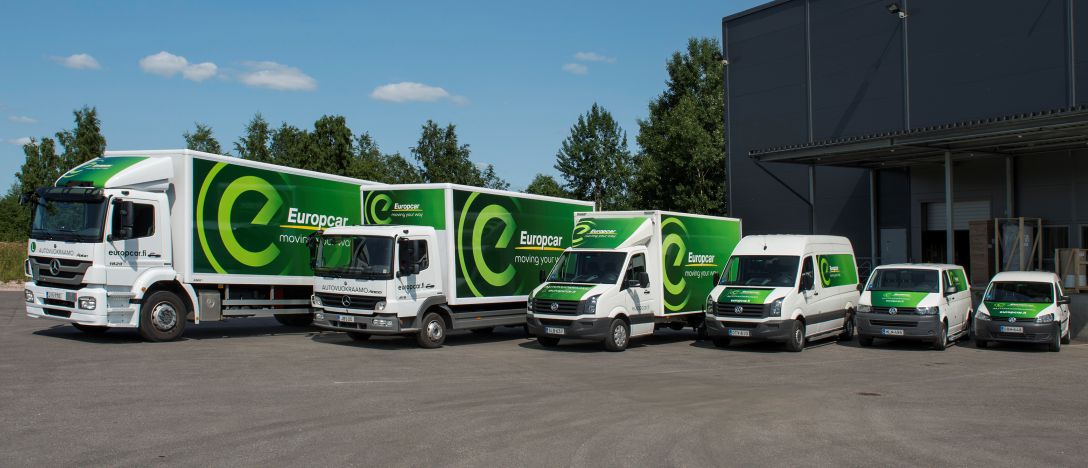
Auch ich habe das e gleich als solches erkannt. Warscheinlich weil hier in der Gegend vermehrt LKW von Europcar unterwegs sind:
Obwohl man natürlich fairerweise sagen muß: Wenn man all die dort inkriminierten Elemente konsequent meidet, wird die Luft ziemlich dünn.
Na ja, aber diese gewissen Moden, die bei der Logogestaltung auftreten, kann man zumindest meiden, so gut es geht. In einer der Agenturen, bei denen ich zu Beginn meines Arbeitslebens angestellt war, hatten wir zum Beispiel »Schwungverbot«. Das war die Zeit, als viele Kunden ankamen und unbedingt einen »Nike«-Schwung in ihrem Logo haben wollten. Nachdem dann alle Möglichkeiten, einen Bogen so unterschiedlich wie möglich zu zeichnen, aufgebraucht waren, und eine Agentur ja auch schlechterdings mit einem, rein mit Schwung-Logos vollgestopften Portfolio auf Neukundenfang gehen kann, durfte keiner mehr mit solchen Stilelementen in seinen Entwürfen beim Kreativchef aufkreuzen.